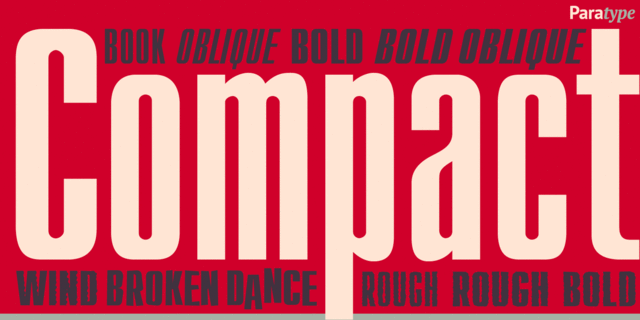
Гарнитура разработана в фирме ПараТайп (ПараГраф) в 1991 (дизайнер Владимир Ефимов) на основе шрифта Анонс (дизайнер Геннадий Барышников). Сверхузкий гротеск. Предназначен для применения в рекламе и акциденции. Декоративные начертания добавлены в 1997 Александром Тарбеевым.